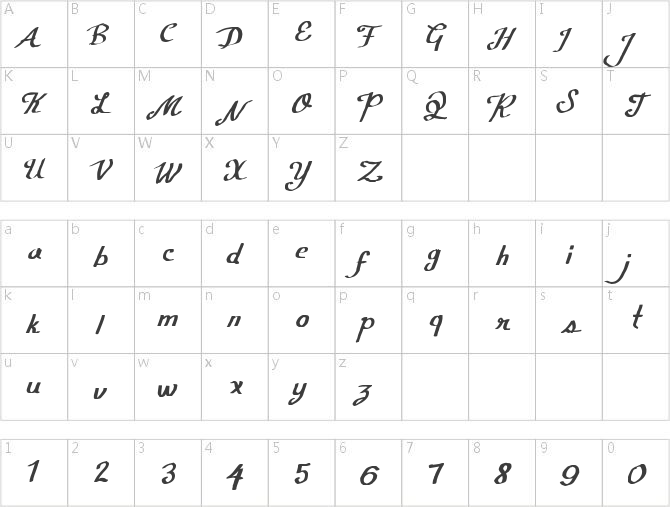
CFCalligraphia-Regular 詳情頁
字體名稱: CFCalli
CFCalligraphia-Regular
CFCalligraphia-Regular字體字庫是一款讓人賞心悅目、百看不厭的英文字體,適合各類廣告和產品包裝設計應用,字體大小0.06MB,格式為ttf字體,上傳用戶是惠祥博達,作者/版權方為未知